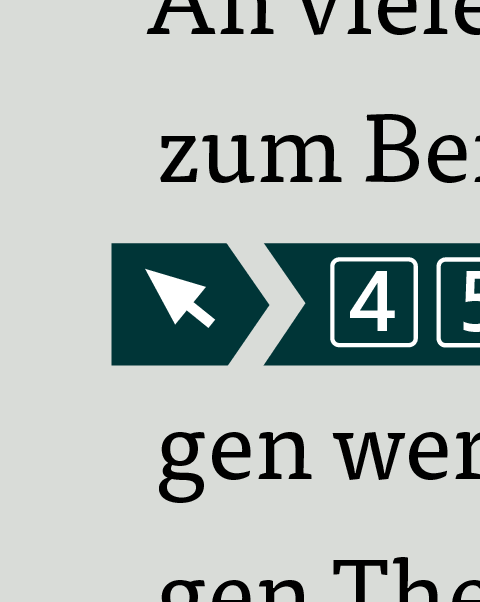
»Jaaaaahhh, *das* kann nur Berthold!« …
… waren die Worte eines ehemaligen Gewerkschaftsfreundes und späteren Kommilitonen zum Thema »Randausgleich« (an der Satzkate). Das ist der optische Ausgleich von herausstehenden bzw. in den Satz hereinragenden Buchstaben wie typischerweise A,S, T, V, W, Y etc, also alle mit viel »Fleisch« vor dem Bug. Und sogar auch schon dahinter: Der Randausgleich funktionierte auf Anhieb auch für die rechte Satzkante und auch für das Divis.
Wann hatte ich ihm die Frage gestellt? Also, ich selbst war zu dem Zeitpunkt selbst noch Setzer an Bertholds Serie M in Frankfurt. Dieses System war als einziges in der Welt in der Lage, diese Funktion vollkommen flüssig, absturzsicher und sogar in Kombination mit kompliziertem Formsatz zu meistern.
InDesign hatte das anfangs auch nicht, dort ist er aber jetzt unter Schrift --> Textabschnitt --> »Optischer Randausgleich« versteckt.
Ich weiß, es gibt Fälle, die gegen den Randausgleich sprechen, z.B. beim Satz von engen Spalten im Zeitungsdruck. Hier wird meines Wissens eher darauf verzichtet.
Aber sonst ist er doch schlicht und ergreifend Pflicht, oder sehe ich das falsch? Wenn es einem schon so komfortabel vom Satzprogramm dargereicht wird? Also, ich kann da nicht widerstehen.
Mich würde interessieren, wie Ihr das handhabt!
Die Funktion ist bei mir standardmäßig aktiviert und moderat justiert (über das Standard-Textrahmen-Objektformat) – bis zum Moment indem sie stört, dann wird sie spezifisch deaktiviert.
… dann wird sie spezifisch deaktiviert.
Und wie machst du das?
Ich hab hier gerade so einen Fall, wo invertierte Glyphen aus der Spalte herausgezogen werden, weil ja nur der Inhalt für den optischen Einzug benutzt wird.  :-(
Gibt es da irgendwas, was nicht nicht in endlose Handarbeit ausartet?
im Absatzformat
> Einzüge und Abstände > Optischen Rand ignorieren
oder
in der Steuerungsleiste
> Pulldownmenü > Optischen Rand ignorieren
ich denke, dass sich das Problem - ohne 'Optischen Rand ignorieren' - besser lösen läßt, indem Du uns eine idml-Datei zur Verfügung stellst.
Über GREP ein Leerzeichen davor schmuggeln mit entsprechend unterschnittenem Zeichenformat versehen und in die Verschachtelung einbauen? Oder steht diese »Grafik« nicht zwangsläufig am Zeilenanfang?
Oder steht diese »Grafik« nicht zwangsläufig am Zeilenanfang?
Das ist halt einfach ein mitfließender Querverweis im Text, der auch hunderte Male in dieser Art auftritt. Fällt er auf den Zeilenrand, sieht’s blöd aus. InDesign berechnet einfach nicht ein, dass die Unterstreichungen (die den Hintergrund bilden) auch eine sichtbare Fläche sein können.
Fällt er auf den Zeilenrand, sieht’s blöd aus. InDesign berechnet einfach nicht ein, dass die Unterstreichungen (die den Hintergrund bilden) auch eine sichtbare Fläche sein können.
Ja, schon verstanden. Ich hätte halt versucht, mit einem nicht hinterlegten Leerraum (oder einem ungefärbten Zeichen :-?) einen »Puffer« zu bauen und das automatisch (aber keine Ahnung, ob das funktioniert :shock:). Sieht dann vielleicht wieder etwas löchrig inmitten einer Zeile aus, oder?
Das ist halt einfach ein mitfließender Querverweis im Text, der auch hunderte Male in dieser Art auftritt. Fällt er auf den Zeilenrand, sieht’s blöd aus.
wenn vor dem - mit einem ZF ausgezeichneten 'Querverweis'-  ein 'harter Zeilenumbruch' (Shift+Enter) gesetzt wird, dann entfällt vorne der 'Optische Randausgleich'.
Allerdings müßte das erst nach Fertigstellung des gesamten Textes gesetzt werden.
[…] wenn vor dem - mit einem ZF ausgezeichneten 'Querverweis'-  ein 'harter Zeilenumbruch' (Shift+Enter) gesetzt wird, dann entfällt vorne der 'Optische Randausgleich'.
Dieses Absatz-Verhalten wäre mir neu. Ich habe es eben ausprobiert und kann den Effekt, dass der optische Randausgleich übergangen wird, mit der beschriebenen Methode nicht nachvollziehen.
Ich hab mal eine idml-Datei hochgeladen.
Vielleicht habe ich ja auch etwas nicht richtig verstanden.